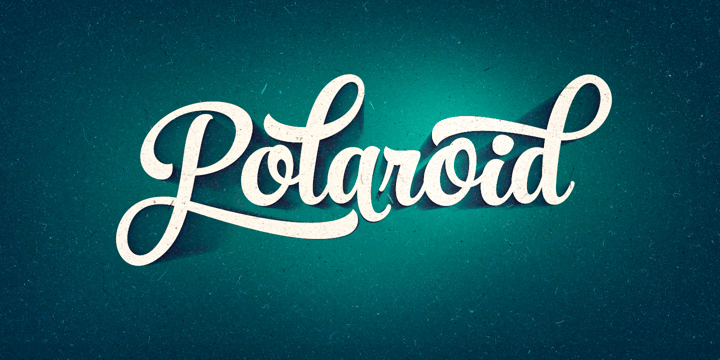
Лучший шрифт для логотипа бренда — выбрать или создать? в Блоге
ОглавлениеШрифт для логотипа — это не просто набор символов и знаков (графем) заданного размера и начертания. Каждый шрифт имеет собственный графический рисунок, которым передает настроение и характер текста. Это именно та форма, которая определяет эмоциональное содержание.
Типографика не всегда обращает на себя внимание, но обязательно оставляет впечатление от слов, которые ею написаны. Эффектность и заявка на премиальность, чувство уверенности и силы, ощущение легкости и искренности — эти и любые другие чувства, вызванные фирменным знаком, во многом определяются стилем его букв.
Поэтому шрифт для логотипа — это один из четырех инструментов (вместе с формой, символом и цветом), которые создают образ бренда для его клиентов и партнеров.
Подобрать шрифт для логотипа: с чего начать?
Каждый шрифт имеет индивидуальность и передает определенное настроение.
Чтобы решить, какой шрифт использовать для логотипа, вначале нужно ответить на базовые вопросы о позиционировании фирмы:
Можно ли в вопросе, как выбрать шрифт для логотипа, ориентироваться на пример глобальных брендов? В некоторых моментах.
Если посмотреть на логотипы всемирно известных корпораций, которые за десятилетия существования приобрели статус love-brands, то в них преобладает один и тот же шрифт — Helvetica.
Чем это объясняют маркетологи?
То что нужно для компании, которая дорожит репутацией и старается нравиться самым разным людям.Сегодня задача выбрать шрифт для логотипа из многообразия доступных может оказаться намного сложнее. Рассмотрим основные виды шрифтов и их свойства:
Если говорить о форме букв, то:
Предложив 3 тысячам респондентов оценить 100 логотипов мировых брендов, международное брендинговое агентство Siegel+Gale выяснило, что легче запоминаются четкие и простые лого.
Если говорить об особенностях восприятия, связанных с типографикой, то эмблемы с геометрическими, рублеными и гротескными графемами были названы мощными.
А шрифт для логотипа с засечками делает его традиционным и консервативным, вызывая уважение.
О чем расскажут размер и наклон букв
Прописные или строчные, курсивные, жирные или подчеркнутые — в графемах можно закодировать существенные смыслы:
Шрифт может стать выразительным и заметным элементом фирменного стиля. Иногда даже определяющим — это зависит от общей концепции айдентики: оригинальные и узнаваемые графемы приобретают большую значимость.
Выбрать шрифт для логотипа: важные правила
Выбор шрифта для логотипа нужно делать, одновременно оценивая его художественную ценность (как изображения) и функциональные возможности.![]()
Ключевые рекомендации:
Выбирая шрифт для логотипа, не стоит ориентироваться только на тренды — они не вечны. Успешный бренд может пережить не один десяток актуальных шрифтов. Целесообразнее исходить из ценностей и позиционирования компании.
Что дает компании собственный оригинальный шрифт?
Интернет предлагает большой простор для экспериментов и много возможностей выбрать крутой и красивый шрифт для логотипа. Есть сервисы подбора, где можно оценить сотни вариантов и понравившийся шрифт для логотипа скачать бесплатно.
Но все эти наборы шрифтов — только базовый рабочий материал.
Стать инструментом для выражения сущности и характера бренда типографика может только в руках профессионала, который владеет приемами дизайна и понимает психологию его восприятия.
глава 2
Как выбрать шрифт для логотипа?
Шрифт является один из наиболее важных элементов логотипа. От него зависит читабельность логотипа, его восприятие, передача главного смысла.
Перед тем, как мы перейдем к основным правилам подбору шрифта для логотипа, давайте рассмотрим, какие есть категории шрифтов и их психологическое восприятие.
Почему важно знать категории шрифтов?
Зная основные типы шрифтов, мы сможем их правильно использовать и комбинировать, а также вызывать нужные эмоции.
Категории шрифтов
1. Шрифты с засечками
2. Шрифты без засечек
3. Рукописные
4. Машинописные
5. Декоративные
1. Шрифты с засечками (Serif) имеют небольшие черточки на концах каждого элемента буквы и переход от толстой линии к более тонкой.
Шрифты с засечками помогают держать внимание читателя на строке.Они наиболее четкие и читабельные
2. Шрифты без засечек не имеют засечек и зачастую бывают правильной геометрической формы с ровными линиями и прямыми углами.
В Англии и Франции такие шрифты называют Sans Serif, в Америке Gothic, в Германии Grotesk.
Шрифты без засечек просты для восприятия из-за своей формы но они практически не подходят для чтения — плохо читабельны. Поэтому шрифты без засечек используют, как правило, только в заголовках. Самые популярные шрифты без засечек — Futura и Helvetica.
3. Рукописные шрифты напоминают текст, написанный вручную ручкой, кисточкой и т.п.
Рукописные шрифты плохо читабельны, поэтому их используют только как заглавные буквы.
CASUAL
Casual дополняет друг друга и может использоваться для личных и коммерческих проектов.
BRUX
Brux — стильный и яркий смелый шрифт с кистью! Он придаст вашим проектам индивидуальность и идеально подходит для цифровой и печатной работы!
ANDIS
Andis — это шрифт, который отлично смотрится в любом размере.
SURCO
Шрифт Surco с ручным штрихом производит впечатление оптимистичного гуманистического шрифта без засечек.